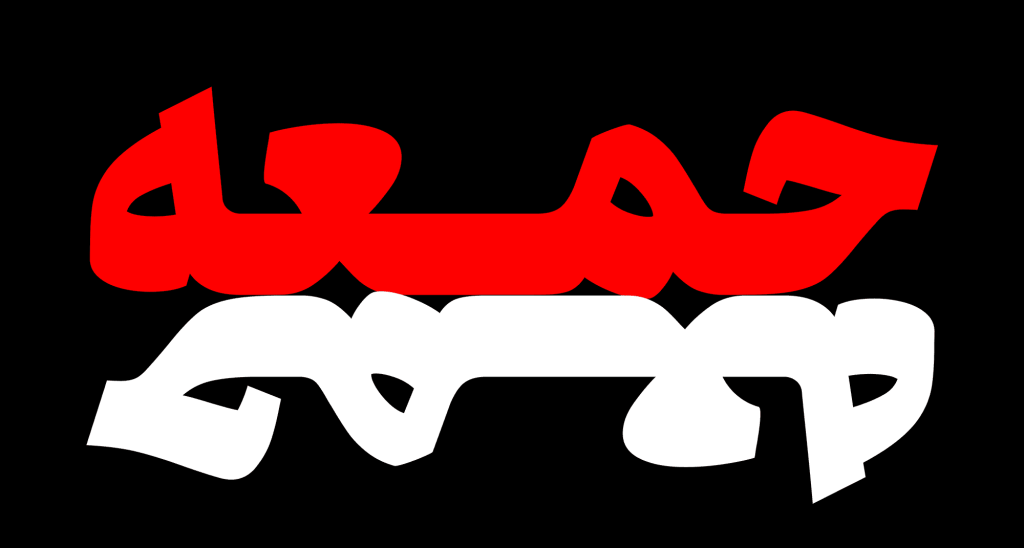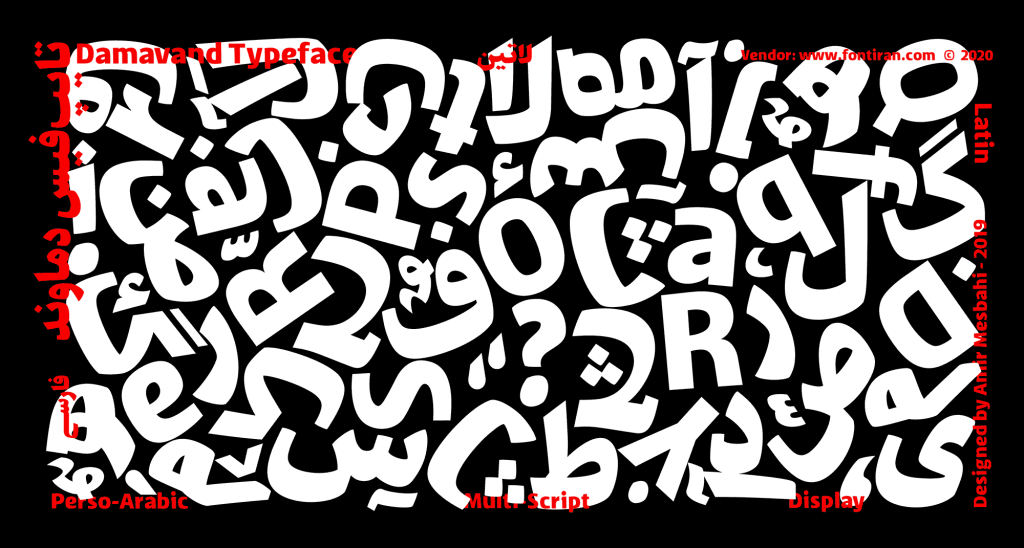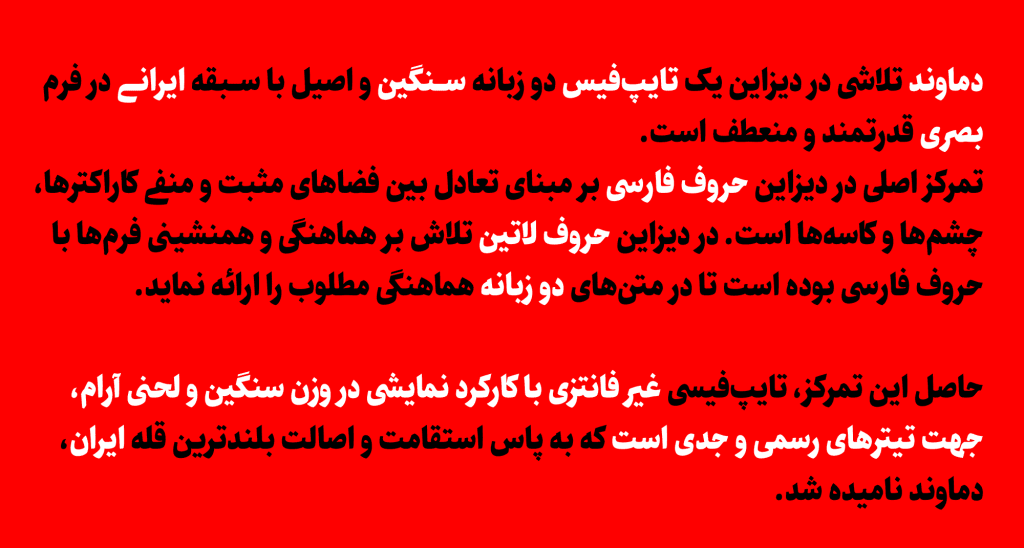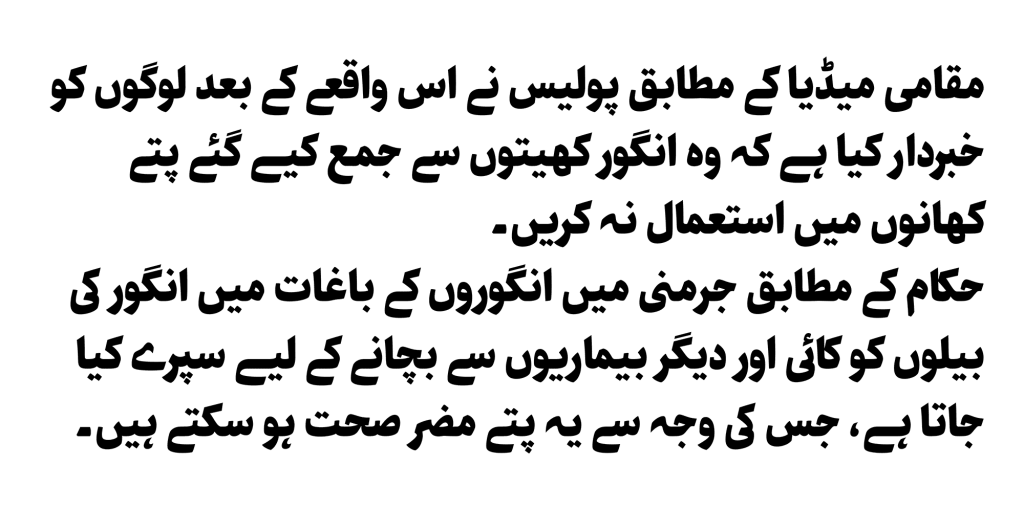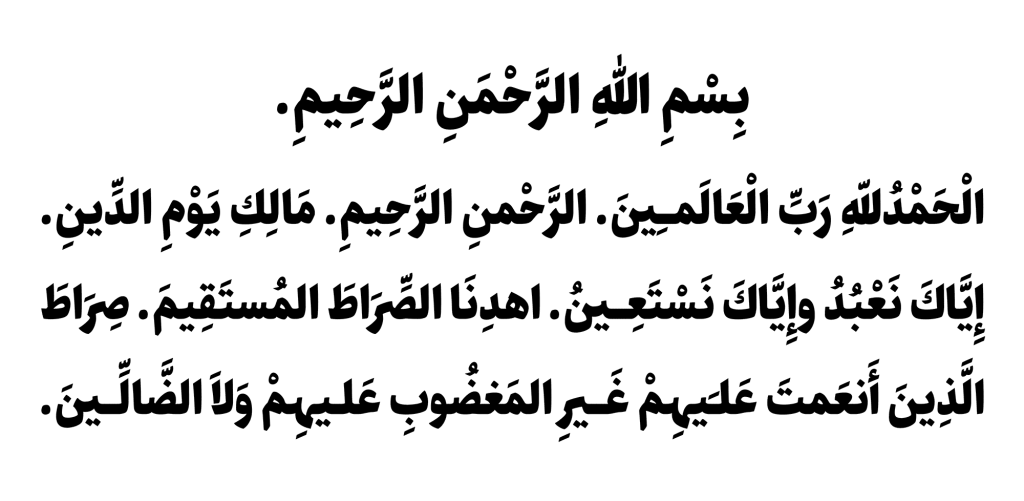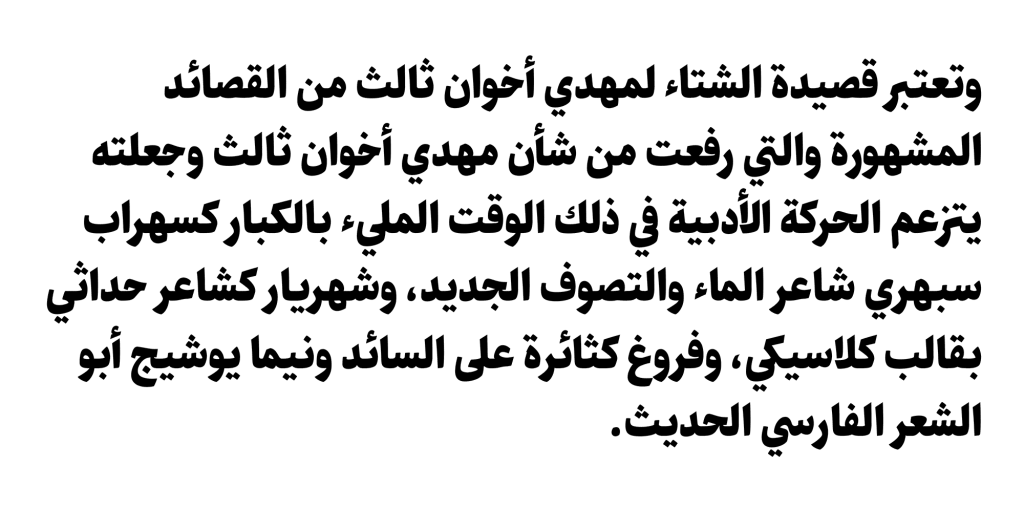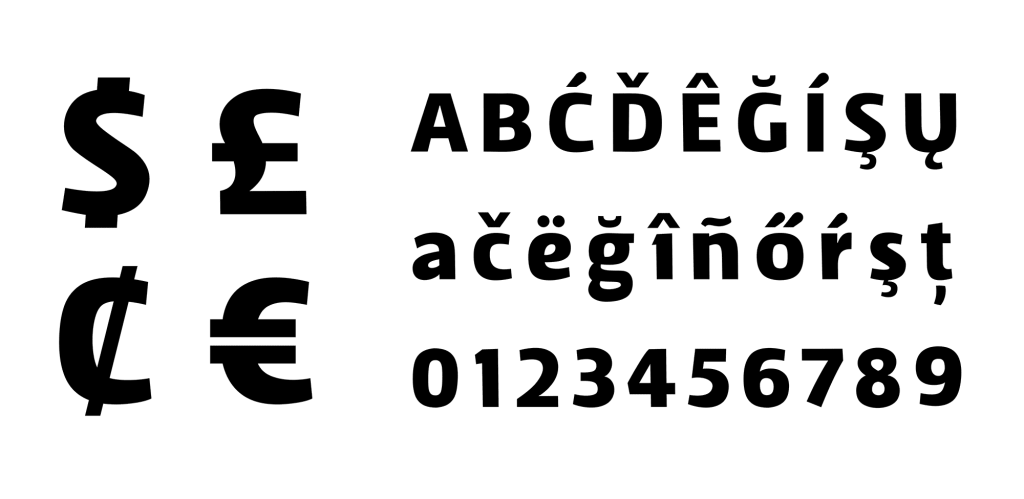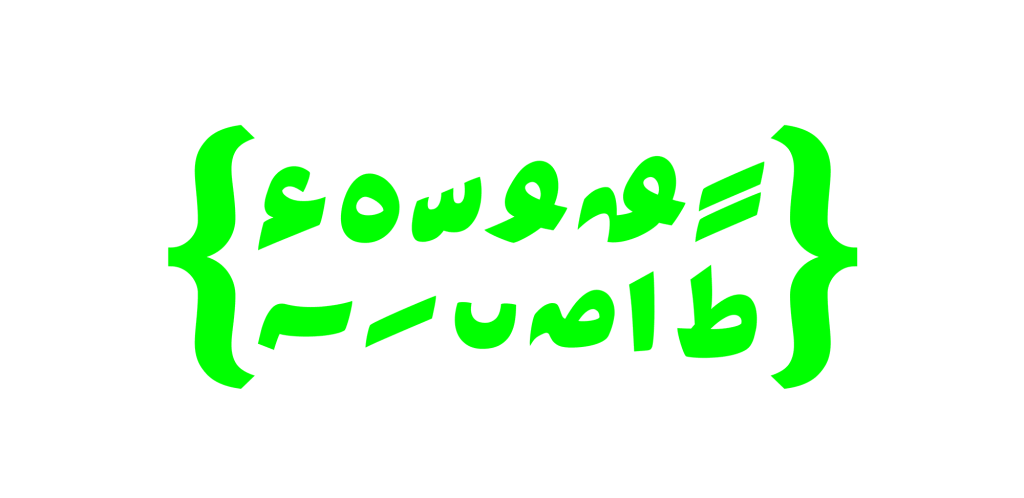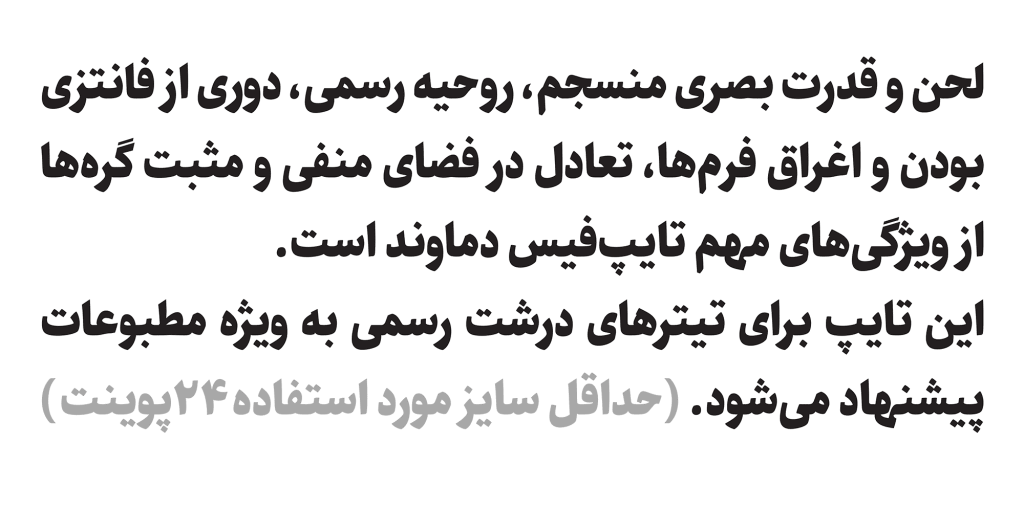
فونت دماوند
در طراحی حروف لاتین فونت دماوند تلاش بر هماهنگی و همنشینی فرمها با حروف فارسی بوده تا حد امکان بوده است تا در متنهای دوزبانه هماهنگی مطلوب را ارائه نماید. نتیجه این تلاش و ممارست، قلمی است غیر فانتزی با کارکرد نمایشی در وزن سنگین و لحنی آرام و نرم ، جهت تیترهای رسمی و جدی است که به تلاش استقامت و اصالت بلندترین قله ایران، دماوند نامیده شد.
از ویژگی های مثال زدنی دماوند لحن و قدرت بصری منسجم، روحیه رسمی، دوری از فانتزی بودن و اغراق فرمها، تعادل در فضای منفی و مثبت گرهها را می توان نام برد. انتخابی بسیار مناسب برای مطبوعات به ویژه تیترهای درشت رسمی و اداری بسیار پیشنهاد میشود.
دماوند شخصیتی بی باک و نمایشی دارد که به دنبال جذب نگاه مخاطبان به خود می باشد . در زیر شما عزیزان می توانید تصاویر مربوط به این قلم زیبا را مشاهده کنید.